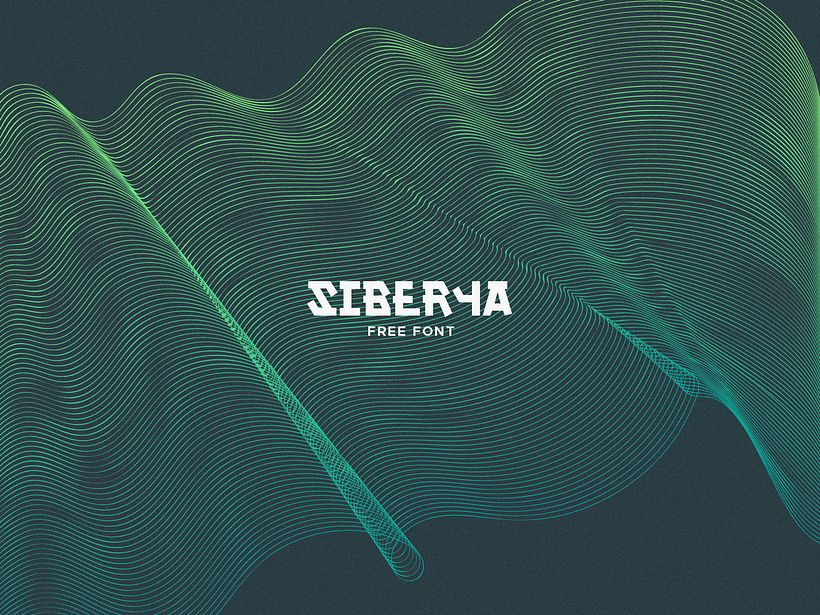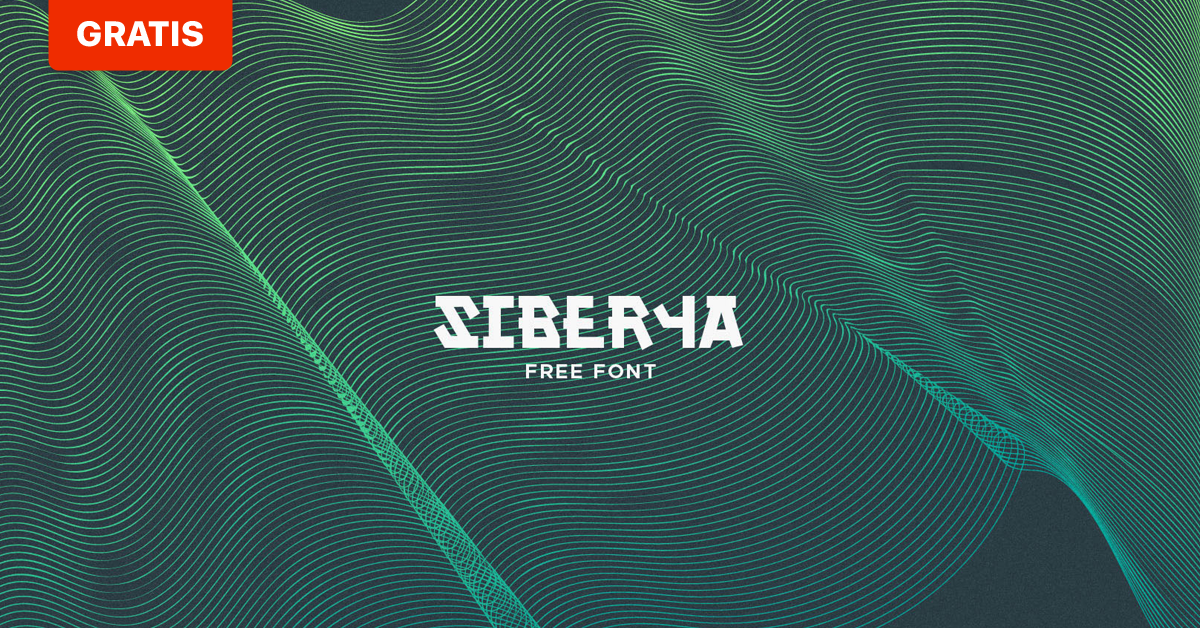
Descarga gratis la tipografía Syberia, de Carlos Liberal
Carlos Liberal comparte con Domestika esta tipografía gratuita inspirada en el alfabeto cirílico y la propaganda soviética.
Siberya es la primera incursión de Carlos Liberal (@carlosliberal) –diseñador y director de arte salmantino– en el diseño tipográfico. La idea de crear su primera tipografía surgió después de cursar un máster de dirección de arte publicitario de la Universidad de Vigo; el tipógrafo Damià Rotger y el calígrafo Oriol Miró –profesional que imparte en Domestika el curso Caligrafía con góticas potentes– le dieron las herramientas necesarias para enfrentarse al diseño de letras y a partir de ese punto de partida decidió embarcarse en la ambiciosa tarea de diseñar su propia tipografía, que hoy comparte con Domestika de manera completamente gratuita.
Nacía, entonces, Siberya, una tipografía inspirada en el alfabeto cirílico y en los tipos de letra utilizados en el cartelismo de la propaganda soviética. Su autor juega con la geometría de las formas que componen esta tipografía y con los pesos que componen estas figuras, rompiendo la monotonía y regularidad por medio de la inclusión de elementos variables. Además, Carlos Liberal ha diseñado el alfabeto en dos pesos.